15 meilleures polices de boxe 2023 (gratuites et premium)
Publié: 2023-08-22Êtes-vous un graphiste à la recherche de la police parfaite pour rehausser le design de vos projets ? Cherchez pas plus loin! Dans cet article de blog, nous vous présentons les 15 meilleures polices de boxe qui donneront à vos créations un look puissant et percutant.
La boxe est un sport connu pour sa force, sa vitesse et son intensité. Tout comme la boxe, ces polices ont du punch et apportent une sensation d’énergie et d’enthousiasme à n’importe quelle conception.
Avec leurs formes de lettres audacieuses et dynamiques, ils sont parfaits pour les titres, les logos, les affiches et tout projet nécessitant une forte présence visuelle.
Dans cet article, nous explorerons en détail les 15 meilleures polices de boxe, en discutant de leurs caractéristiques uniques et en présentant des exemples de la façon dont elles peuvent être utilisées efficacement.
Que vous travailliez sur un projet lié au sport, une publicité de fitness ou que vous souhaitiez simplement ajouter un impact visuel à votre conception, ces polices impressionneront à coup sûr.
Alors, allons-y et découvrons les polices qui feront passer votre jeu de conception au niveau supérieur !
Meilleures polices de boxe premium
Êtes-vous un graphiste qui cherche à ajouter du punch à vos projets ? Ne cherchez pas plus loin que notre collection des 15 meilleures polices de boxe. Ces polices haut de gamme sont garanties pour avoir du punch et élever vos créations au niveau de championnat.
Ne manquez pas l'occasion de découvrir et d'en savoir plus sur ces polices incroyables dans la section suivante !
Boxeur
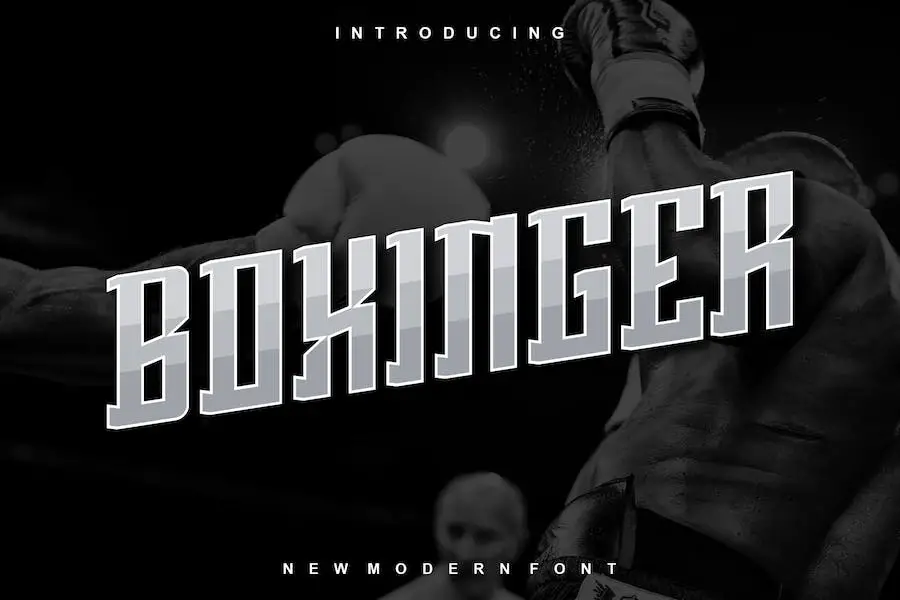
Boxinger est une police d'affichage audacieuse et authentique connue sous le nom de « It Font – Modern Font ». Il est parfait pour les graphistes qui cherchent à améliorer leurs projets avec une touche de design inspiré de la boxe.
Que vous travailliez sur un logo, l'impression de t-shirts, l'e-sport ou tout autre projet de marque, cette police fera certainement une déclaration.
Avec son apparence forte et percutante, Boxinger se démarque dans des contextes variés. Son style moderne et audacieux ajoute une touche unique à vos créations, les rendant visuellement attrayantes et accrocheuses.
Cette police a pour but de faire une déclaration audacieuse et de laisser une impression durable à votre public.
L'un des grands avantages de Boxinger est sa compatibilité avec des outils de conception comme Canva et Cricut. Avec l’essor des plateformes de conception en ligne, il est essentiel de disposer d’une police qui s’intègre parfaitement à ces outils.
À l'intérieur de la boîte
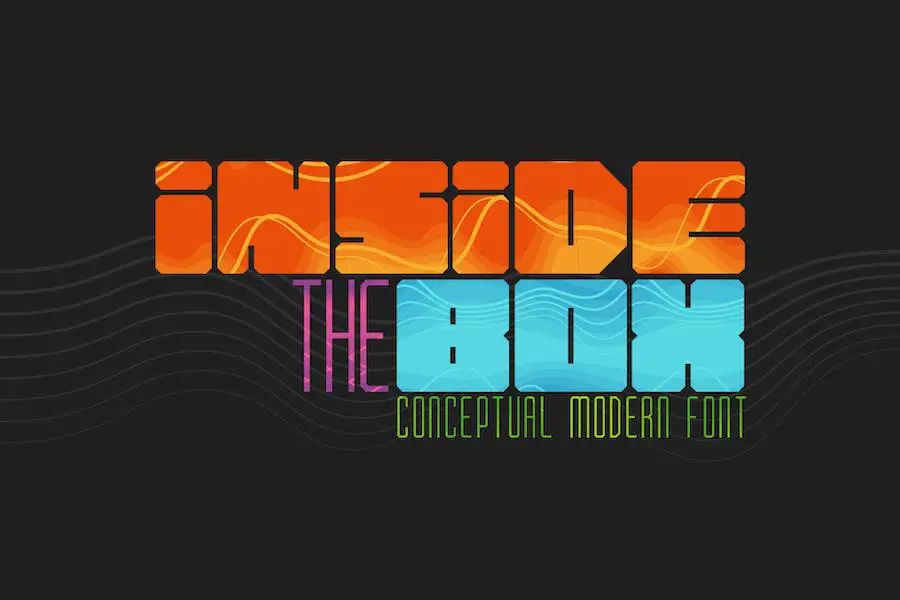
À l’intérieur de la BOX se trouve une police conceptuelle moderne qui apporte une touche unique à vos projets de conception graphique. Cette police deux-en-un comporte des lettres majuscules grasses et grasses, tandis que les lettres minuscules sont fines.
Avec son esthétique moderne et audacieuse, il est parfait pour créer des designs accrocheurs pour des projets liés à la boxe.
Le contraste entre les lettres majuscules audacieuses et les lettres minuscules fines crée un effet visuellement intéressant, vous permettant de jouer avec différents éléments de design et de créer une composition dynamique.
Que vous conceviez un logo, un t-shirt ou une bannière promotionnelle, cette police apportera une touche moderne et stylée à votre projet.
Avec Inside the BOX, vous pouvez facilement personnaliser la taille et l'espacement des lettres pour répondre à vos besoins de conception. Sa polyvalence vous permet de l'utiliser comme point focal principal ou comme élément complémentaire pour rehausser votre design global.
Boxe invisible
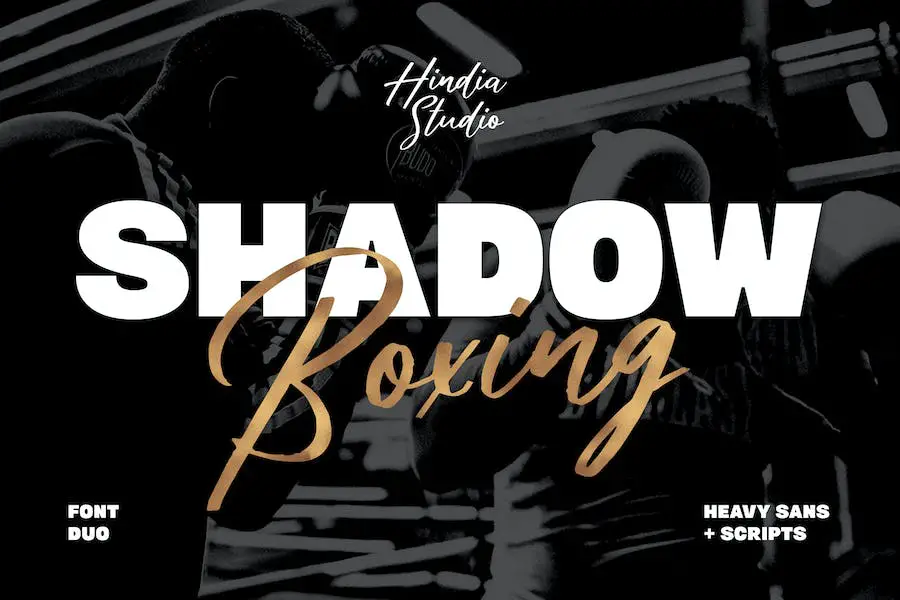
Shadow Boxing est le duo de polices ultime qui combine un puissant sans empattement avec un script au pinceau insouciant. Avec son mélange unique de styles, Shadow Boxing est parfait pour les designers qui souhaitent faire une déclaration audacieuse dans leurs projets.
Que vous ayez besoin d'une police forte et percutante pour une affiche, un logo ou tout autre design, Shadow Boxing est là pour vous.
La police sans empattement de Shadow Boxing respire la force et le professionnalisme. Ses lignes épurées et ses bords nets donnent à votre texte un aspect moderne et épuré. Utilisez-le pour créer des titres, des titres ou tout autre texte qui doit attirer l'attention et faire forte impression.
D'autre part, la police de script au pinceau dans Shadow Boxing ajoute une ambiance ludique et insouciante à vos créations. Son style dessiné à la main et son aspect organique apportent une sensation de chaleur et de personnalité.
Parfaite pour ajouter une touche manuscrite ou décontractée à vos créations, cette police de script est polyvalente et peut être utilisée dans divers projets de conception.
Boxe
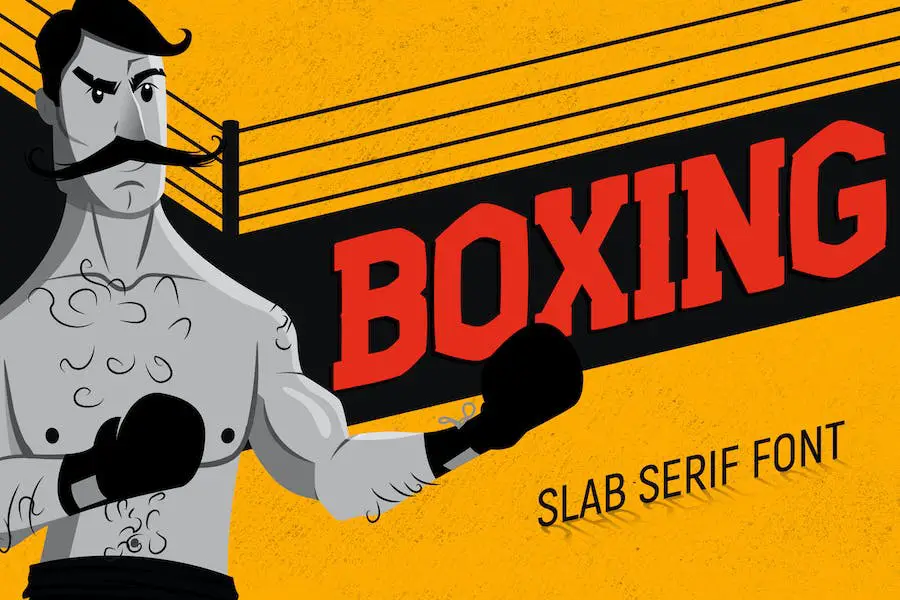
Boxing est une police slab serif amusante et prête à se battre ! Inspirée du sport et des jeux, cette police a un look audacieux qui mettra en valeur vos créations.
Que vous créiez une affiche de match de boxe ou conceviez des graphiques pour un événement de jeu, Boxing est le choix idéal pour apporter de l'enthousiasme et de l'énergie à vos projets.
Avec son apparence forte et robuste, cette police respire la puissance et la détermination. Les formes de lettres épaisses et audacieuses le distinguent, garantissant que votre design attirera l'attention des spectateurs.
L’un des grands atouts de la boxe est sa polyvalence. Il fonctionne bien dans une gamme de projets et peut être utilisé dans divers contextes.
Que vous souhaitiez créer une affiche d'inspiration vintage ou un logo de jeu moderne, cette police peut s'adapter à vos besoins. Son audace et sa personnalité en font un choix idéal pour un large éventail de projets de design.
BOITE Aérée
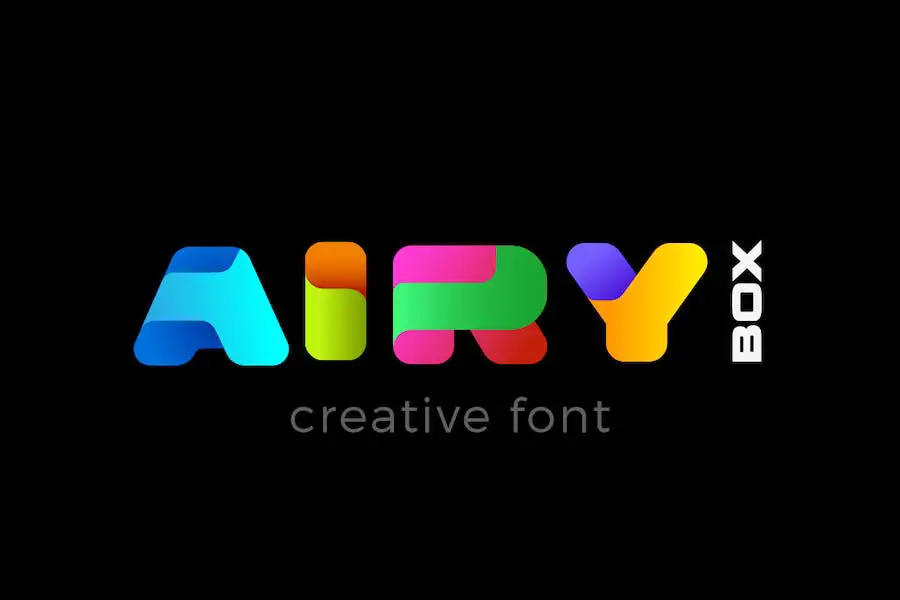
Airy BOX est une police créative conviviale et innovante, qui est un rebond de la police populaire Airy. Il offre une option de conception rafraîchissante et unique pour les graphistes qui cherchent à rehausser l'attrait visuel de leurs projets avec une touche de créativité.
Cette police possède une gamme d’attributs qui en font un choix incontournable pour les concepteurs. Premièrement, son caractère convivial et accessible le rend polyvalent et adapté à un large éventail de projets.
Que vous conceviez une affiche, un logo ou des graphiques pour les réseaux sociaux, Airy BOX améliorera sans effort l'esthétique globale de votre projet.
De plus, Airy BOX est riche en créativité et en innovation, ce qui en fait un excellent choix pour les designers qui souhaitent repousser les limites et expérimenter des styles uniques. Ses éléments de design distincts et accrocheurs captiveront votre public et laisseront une impression durable.
Boîte brumeuse
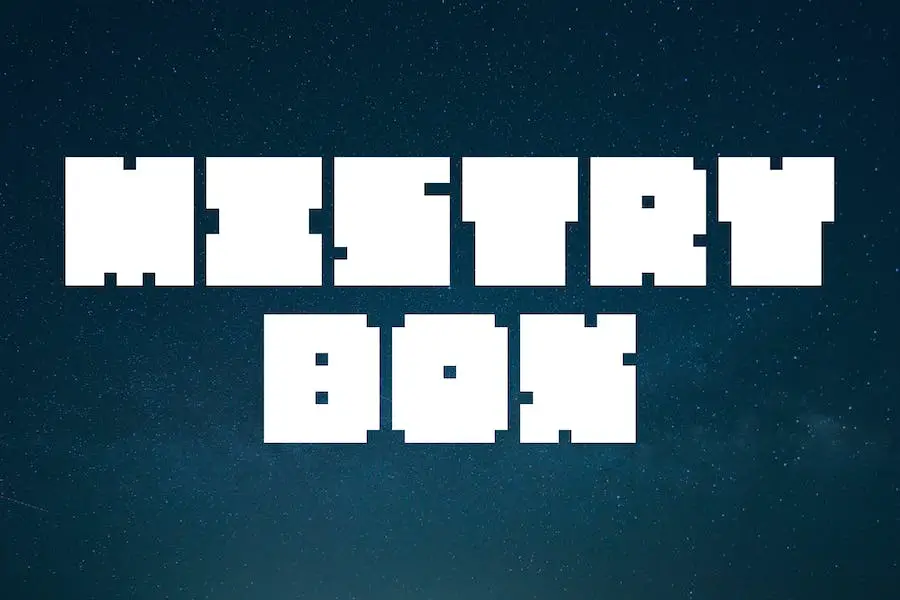
Mistry Box est une police d'affichage épaisse et audacieuse, parfaite pour créer des designs percutants. Avec son apparence audacieuse et puissante, c'est un excellent choix pour les grands titres, les marques, les logos et bien plus encore.
Sa polyvalence en fait une police incontournable pour les graphistes cherchant à ajouter du punch à leurs projets.
Cette police de boxe respire la confiance et la force, ce qui la rend idéale pour les designs qui doivent faire une déclaration audacieuse. Que vous travailliez sur un projet lié au sport, créiez un logo saisissant ou conceviez une affiche visuellement captivante, Mistry Box est là pour vous.
Avec ses lettres épaisses et audacieuses, Mistry Box attire l'attention et se démarque de la foule. Il ajoute une touche de style et de professionnalisme à n’importe quel design et garantit une impression durable.
Hégard
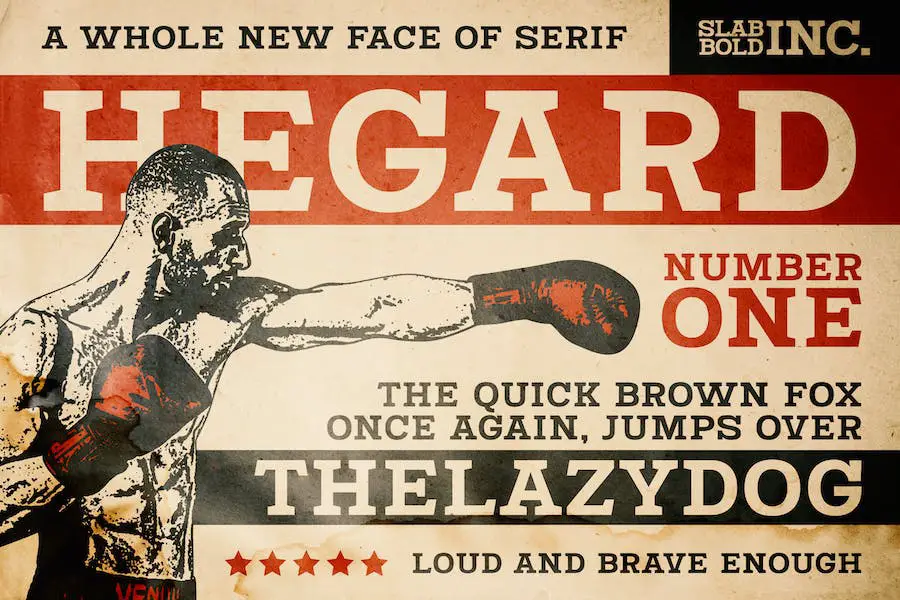
Hegard est une police qui s'inspire des affiches de boxe vintage des années 80. Il incarne une déclaration forte et audacieuse, vous permettant de faire ressortir votre voix courageuse dans vos projets de conception graphique visuelle.
Avec Hegard, vous pourrez capturer l'essence de l'époque des années 80 et l'infuser dans vos créations. Sa présence forte et imposante fera une déclaration audacieuse et attirera l’attention de votre public.
Cette police est parfaite pour les projets qui nécessitent une ambiance forte et courageuse. Que vous conceviez une affiche sportive, un logo pour une marque de fitness ou que vous créiez des titres audacieux pour votre site Web, Hegard sera le partenaire idéal dans le crime.
Kick-boxing
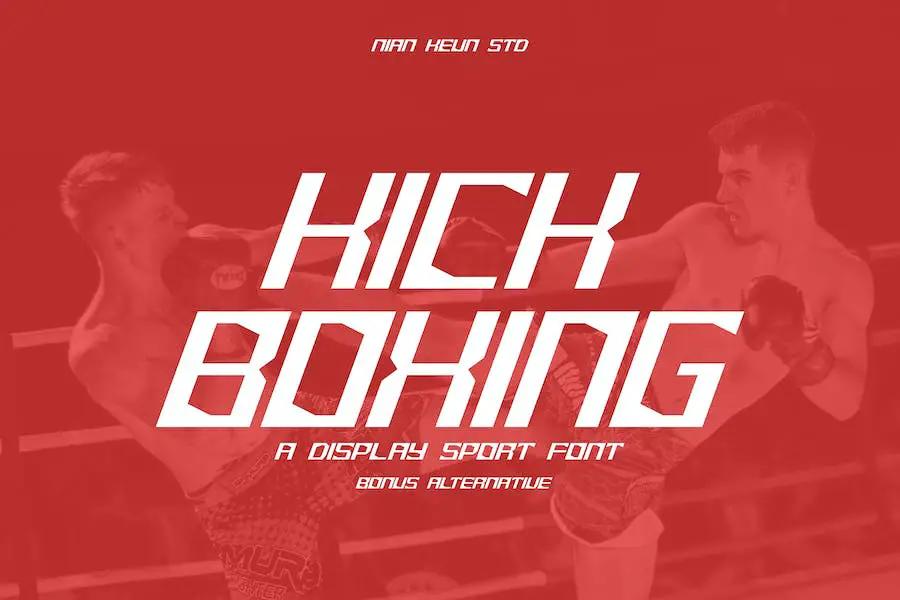
Kick Boxing est un affichage de polices sportives qui s'inspire du monde de la boxe. Son design intègre la vitesse et la puissance associées au sport, avec un style incliné qui reflète le mouvement énergique d'un boxeur. Il en résulte une police vraiment unique et accrocheuse.
L'inclinaison du Kick Boxing lui donne une forme distincte, ce qui le rend parfait pour les projets nécessitant un design fort et percutant.
Que vous créiez un logo pour une salle de boxe, conceviez du matériel promotionnel pour un événement sportif ou travailliez sur un projet lié au fitness, cette police ajoutera une touche d'enthousiasme et d'énergie.
Avec son apparence dynamique et audacieuse, Kick Boxing se démarque certainement des autres polices. Son caractère et son style en font un choix idéal pour tout projet nécessitant un design puissant et visuellement saisissant.
Scout
Scout est une police athlétique nette, propre et audacieuse, parfaite pour tous vos besoins en matière de marque sportive. Que vous conceviez des emblèmes, des maillots, des affiches, des vêtements, des titres de magazines ou des étiquettes, cette police d'affichage polyvalente ajoutera une touche forte et puissante à vos projets.
Grâce à ses fonctionnalités entièrement crénées et prêtes à l'emploi, vous pouvez commencer à utiliser Scout dès la sortie de la boîte.
Cette police est incroyablement polyvalente, ce qui la rend adaptée à un large éventail de projets de conception. Son style pointu et audacieux ajoute une sensation d'énergie et de dynamisme à toute image de marque liée au sport.
Que vous créiez un logo pour une équipe professionnelle, conceviez des maillots personnalisés pour un club sportif local ou même travailliez sur un magazine ou une affiche sur le thème du sport, Scout fera ressortir vos créations.
L’une des caractéristiques remarquables du Scout est son apparence nette et nette. Les lignes épurées et les bords précis rendent la police très lisible, même dans des tailles plus petites. Cela le rend idéal pour une utilisation dans les titres ou les étiquettes, où la lisibilité est cruciale.
Poing de fer
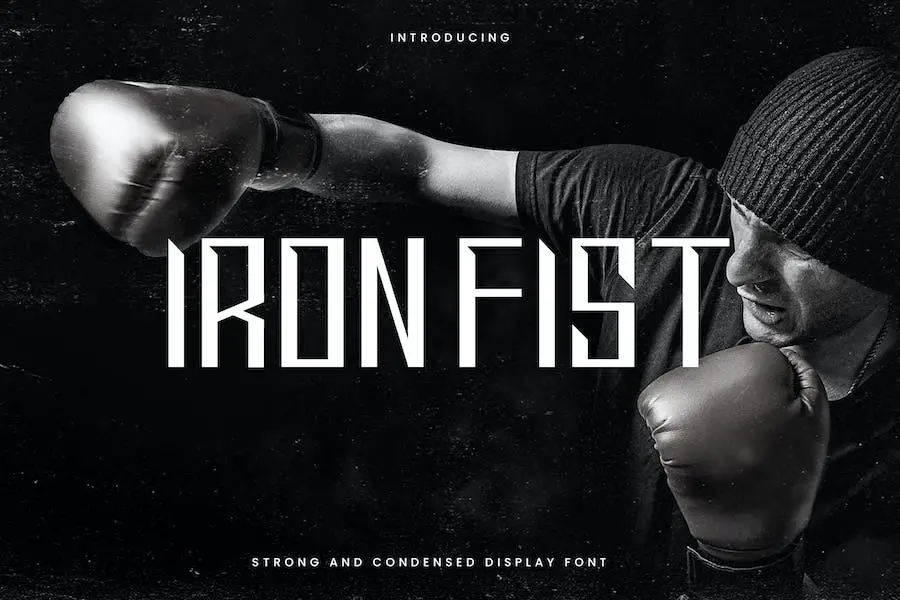
Présentation d'Ironfist, un puissant affichage condensé sans police avec un visuel géométrique élégant. Que vous créiez des invitations, des bannières, des titres de films, des marques ou des événements, cette police est parfaite pour ajouter une touche de force et de sophistication à vos projets.
Avec son design élégant et élégant, Ironfist offre un look unique et accrocheur qui ne manquera pas d'impressionner. Sa forme condensée permet un impact maximal, ce qui le rend idéal pour les titres et les titres.
De plus, son visuel géométrique ajoute une touche moderne et tendance, parfaite pour rester au courant des dernières tendances design.
L’une des meilleures caractéristiques d’Ironfist est sa polyvalence. Cette police convient à diverses occasions, vous permettant de l'utiliser pour un large éventail de projets.
Que vous conceviez une invitation pour un événement haut de gamme ou que vous créiez un titre de film saisissant, Ironfist rehaussera sans effort votre design et fera une impression durable.
Meilleures polices de boxe gratuites
Vous cherchez à ajouter un style saisissant à vos projets de conception ? Ne cherchez pas plus loin que notre collection des 15 meilleures polices de boxe ! Qu’elles soient audacieuses et percutantes ou élégantes et stylées, ces polices donneront certainement du punch à vos créations.
Ne manquez pas les options gratuites que nous avons rassemblées pour vous – consultez-les et laissez votre créativité entrer en scène !
Boîte aux lettres
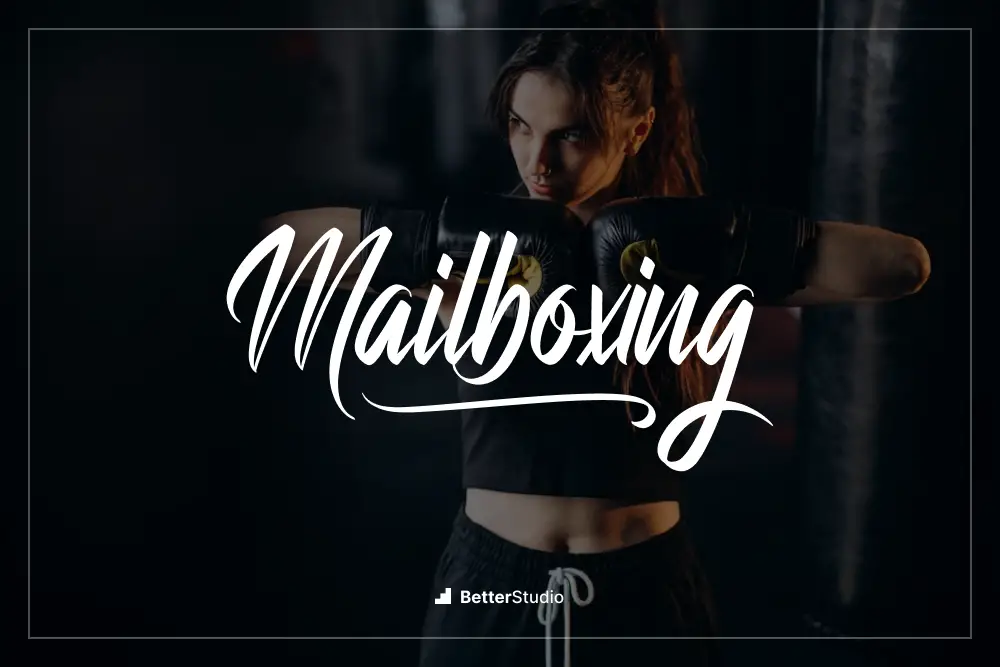
Mailboxing de NihStudio est une remarquable collection de polices de boxe que les graphistes peuvent utiliser pour améliorer la conception de leurs projets.
Ces polices sont spécialement conçues pour ceux qui souhaitent intégrer un thème de boxe dans leurs œuvres, que ce soit pour un tatouage, une affiche ou toute autre entreprise créative.
Les polices présentées dans Mailboxing sont soigneusement conçues pour capturer l'essence de la boxe. Ils respirent la force, la puissance et l’esprit alimenté par l’adrénaline que représente la boxe.
Avec une grande variété de styles, allant de l'audacieux et agressif à l'élégant et élégant, ces polices offrent des possibilités infinies pour ajouter une touche de boxe à n'importe quel design.
Goldie Boxe
Goldie Boxing de Balpirick Studio est une police fantastique, parfaite pour les graphistes cherchant à améliorer la conception de leurs projets. Il s’agit d’une police gratuite qui peut être utilisée pour un usage personnel, ce qui en fait une option attrayante pour les concepteurs à petit budget.
Avec Goldie Boxing, vous aurez accès à une variété de lettrages élégants et uniques inspirés de la boxe. Cette police est spécialement conçue pour les professionnels de l'industrie de la boxe ou les passionnés qui souhaitent ajouter une touche audacieuse et percutante à leurs créations.
Les attributs de Goldie Boxing la distinguent des autres polices. Ses lettres fortes et agressives lui confèrent une apparence puissante et dynamique. Cette police respire l'énergie et l'intensité, ce qui la rend idéale pour les conceptions liées au sport ou tout projet nécessitant une déclaration audacieuse.
Boxe invisible
Shadow Boxing est une police remarquable créée par dcoxy – Greg Medina. Il est disponible pour un usage personnel gratuit, ce qui en fait un choix fantastique pour les graphistes cherchant à améliorer la conception de leurs projets.
Cette police offre un style unique et captivant qui peut apporter une touche d’enthousiasme et de créativité à n’importe quel design.
Avec Shadow Boxing, vous pouvez ajouter un élément visuellement attrayant et dynamique à vos projets. Le design audacieux et audacieux de la police lui confère une impression de puissance et d'impact, parfaite pour capter l'attention et faire une déclaration.
Que vous travailliez sur un design sur le thème de la boxe ou que vous souhaitiez simplement ajouter un peu d'énergie à votre projet, cette police est un excellent choix.
Neutrons
Neutrons est une police unique proposée par CalligraphyFonts.net. C'est une police gratuite qui peut être utilisée pour des projets personnels. Neutrons présente un design calligraphique élégant et moderne, parfait pour ajouter une touche d'élégance à vos projets de conception graphique.
Les attributs de Neutrons incluent ses lignes épurées et élégantes, ce qui le rend idéal pour créer des titres et des titres accrocheurs. Les traits audacieux et expressifs de la police lui confèrent un aspect saisissant et distinctif, la distinguant des autres polices.
Avec son style polyvalent et contemporain, Neutrons peut être utilisé dans une variété de projets de conception, des logos aux affiches en passant par les en-têtes de sites Web.
Ce qui distingue Neutrons, c'est son souci du détail et de son savoir-faire. Chaque lettre est magnifiquement fabriquée à la main, mettant en valeur le savoir-faire et le talent artistique nécessaires à la création de cette police. L'équilibre judicieux des traits et des swashes ajoute une sensation de sophistication et d'élégance à n'importe quel design.
Dragon de boxe
Boxing Dragon est une police dynamique et accrocheuse, parfaite pour les graphistes cherchant à améliorer leurs projets. Créée par Muhammad Iqbal Faizin, cette police est idéale pour ajouter une touche audacieuse et puissante à n'importe quel design.
Les attributs de Boxing Dragon incluent ses formes de lettres fortes et audacieuses, qui font une déclaration et attirent l'attention. Les bords nets et les lignes épurées de la police lui confèrent un look moderne et audacieux qui peut apporter une sensation d'énergie et d'enthousiasme à n'importe quel design.
Qu'il soit utilisé pour les titres, les logos ou les superpositions de texte, Boxing Dragon ajoute une touche de puissance et d'intensité.
Ce qui distingue Boxing Dragon, c'est sa polyvalence. Bien qu'il soit parfait pour les événements sportifs et les promotions, il peut également être utilisé dans divers autres projets de conception tels que des affiches, des images de marque et même des emballages.
Son style distinctif et ses qualités accrocheuses en font une police sur laquelle les concepteurs peuvent compter pour faire une impression durable.
Questions fréquemment posées
Les polices de boxe sont des polices ou des styles typographiques inspirés du sport de la boxe. Ils se caractérisent par leurs lettres audacieuses et fortes, ressemblant souvent aux lettres vues sur les affiches, les publicités et les logos de boxe.
Ces polices peuvent ajouter une impression de puissance et de robustesse à tout design lié à la boxe ou aux sports de combat.
L'utilisation et la licence des polices de boxe peuvent varier en fonction du concepteur de polices et de la police spécifique que vous choisissez. Certaines polices peuvent être gratuites pour un usage personnel et commercial, tandis que d'autres peuvent nécessiter une licence ou un achat pour un usage commercial.
Il est important de vérifier les informations de licence fournies avec chaque police pour vous assurer que vous l'utilisez de manière appropriée pour votre projet commercial prévu.
Les polices de boxe ont gagné en popularité en raison de leur capacité à capturer l’essence du sport et à transmettre un sentiment de force, de détermination et d’enthousiasme.
Ces polices contribuent à créer un impact visuel et à attirer l’attention, ce qui les rend idéales pour concevoir des graphiques accrocheurs liés à la boxe. De plus, les polices de boxe ajoutent une touche d’authenticité et de caractère à la représentation visuelle globale du contenu lié à la boxe.
Conclusion
Pour résumer, dans cet article, nous avons discuté de 15 des meilleures polices de boxe disponibles pour les graphistes cherchant à améliorer la conception de leurs projets. Nous avons exploré une variété de polices qui capturent l’essence de la boxe et transmettent un fort impact visuel.
Si vous avez trouvé cet article utile et souhaitez en savoir plus, n'oubliez pas de consulter le blog de BetterStudio pour des didacticiels plus connexes et du contenu informatif.
N'oubliez pas que la bonne police peut transformer vos créations et les faire vraiment se démarquer. Expérimentez différentes options et n’ayez pas peur de sortir des sentiers battus. Bonne conception !